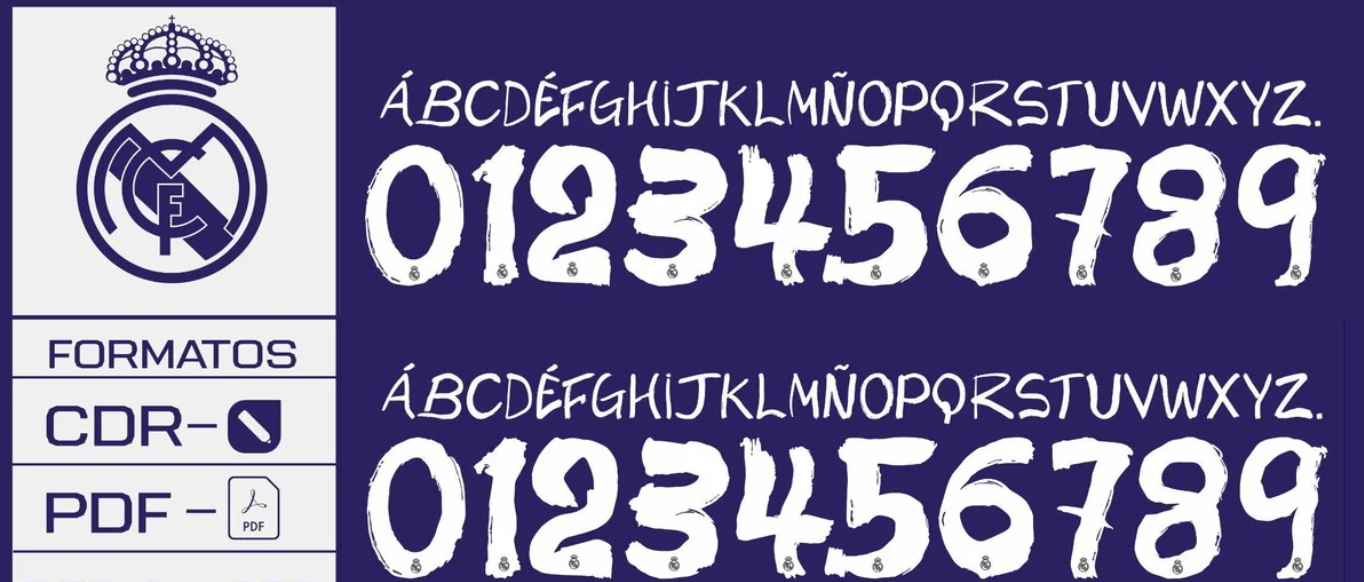
Quando o futebol encontra a alta moda, o resultado é sempre icônico. A parceria contínua entre o Real Madrid, a Adidas e o lendário estilista japonês Yohji Yamamoto (através da marca Y-3) trouxe para a temporada 2024 uma das coleções mais aguardadas pelos designers e torcedores merengues.
Neste post, você tem acesso à tipografia exclusiva utilizada no quarto uniforme (4th Kit) do clube espanhol — aquele marcado pela elegância da cor roxa e o design de rosas — permitindo que você recrie personalizações com o mesmo toque de luxo e exclusividade visto nos gramados europeus.
Estilo Visual e Aplicação
A fonte Y-3 para o Real Madrid foge completamente do padrão das fontes institucionais da La Liga ou das tipografias tradicionais da Adidas. Ela carrega o DNA de Yohji Yamamoto: uma estética que remete à escrita manual, com traços que simulam pinceladas ou o uso de marcadores artísticos.
Esse estilo “imperfeito” e orgânico traz uma sensação de movimento e autenticidade para o uniforme. É a escolha perfeita para quem deseja fugir do óbvio e aplicar um visual premium e fashion em camisas de futebol, mockups ou artes para redes sociais focadas no público streetwear esportivo.
Dica de Uso: Devido ao estilo irregular da fonte, preste atenção redobrada ao alinhamento vertical dos números e nomes nas costas da camisa para manter a harmonia visual proposta pela marca.